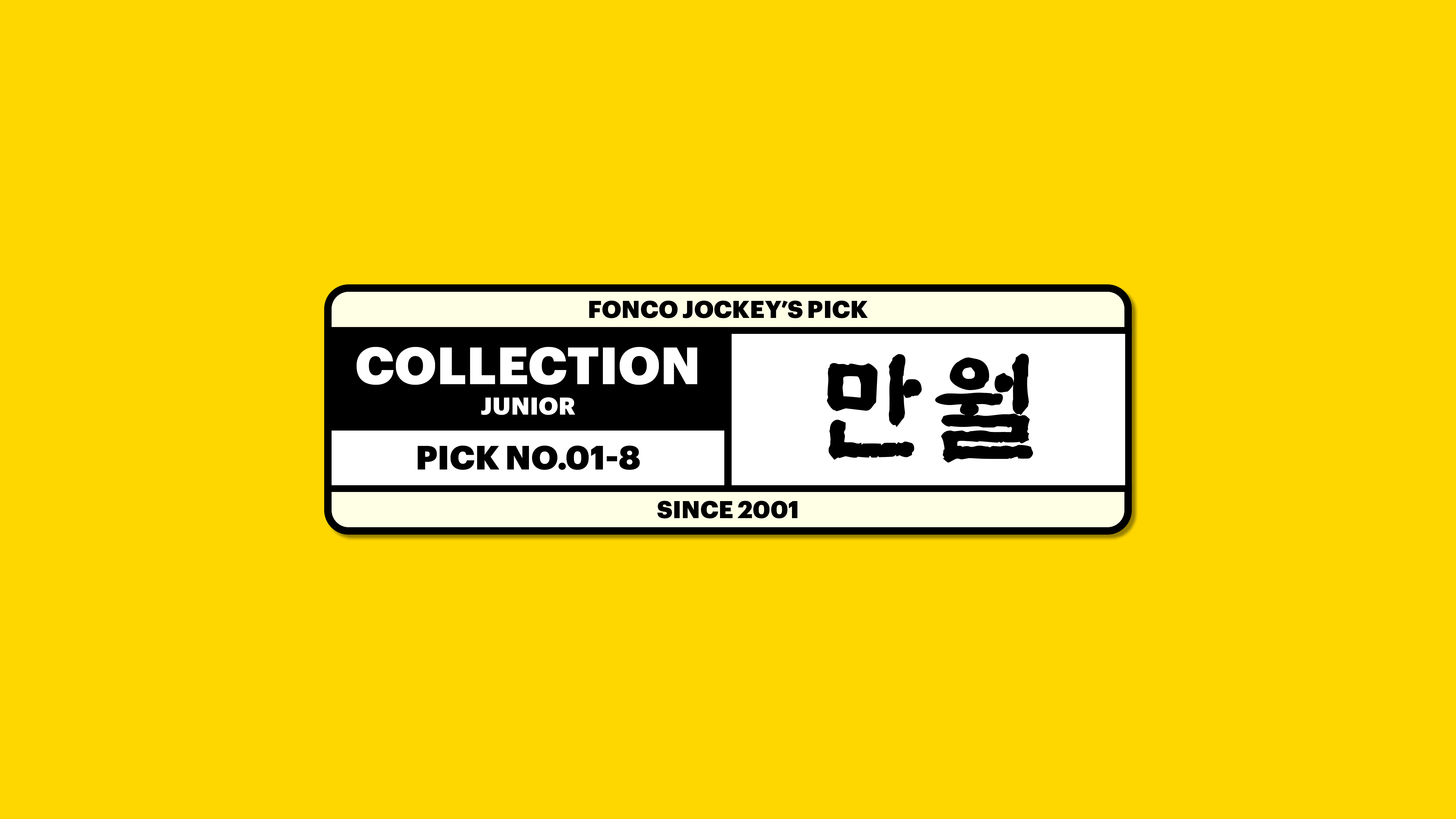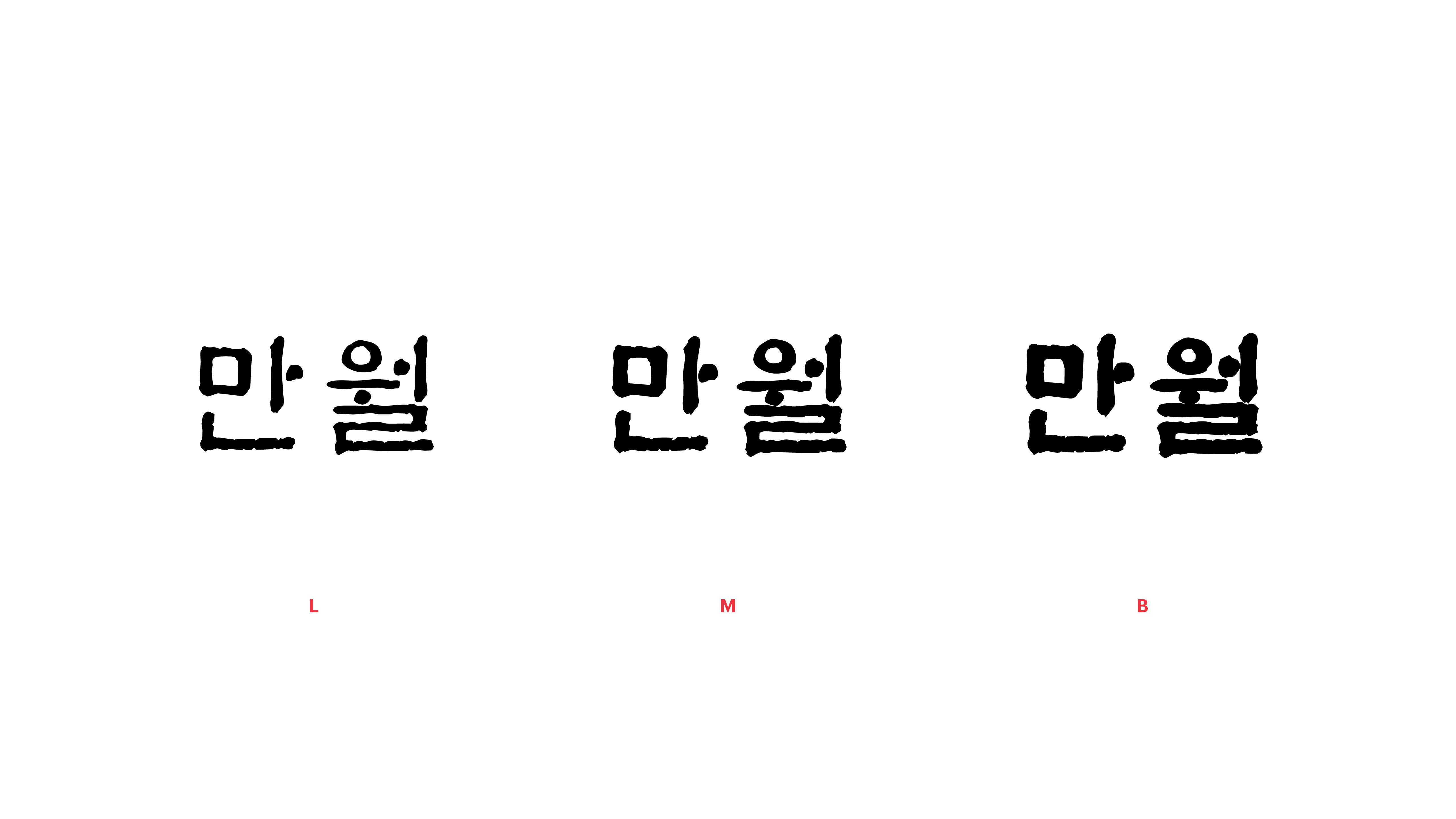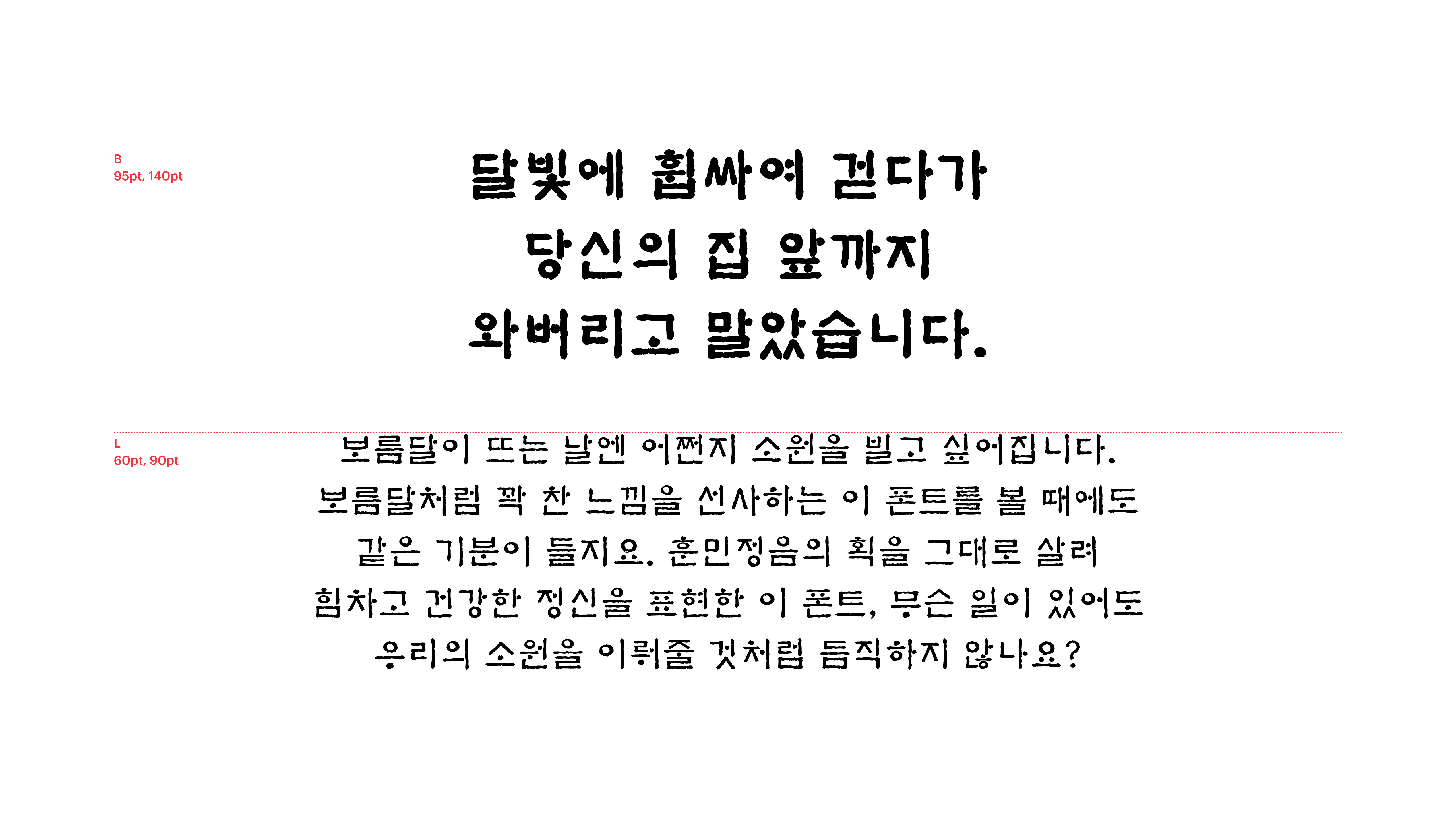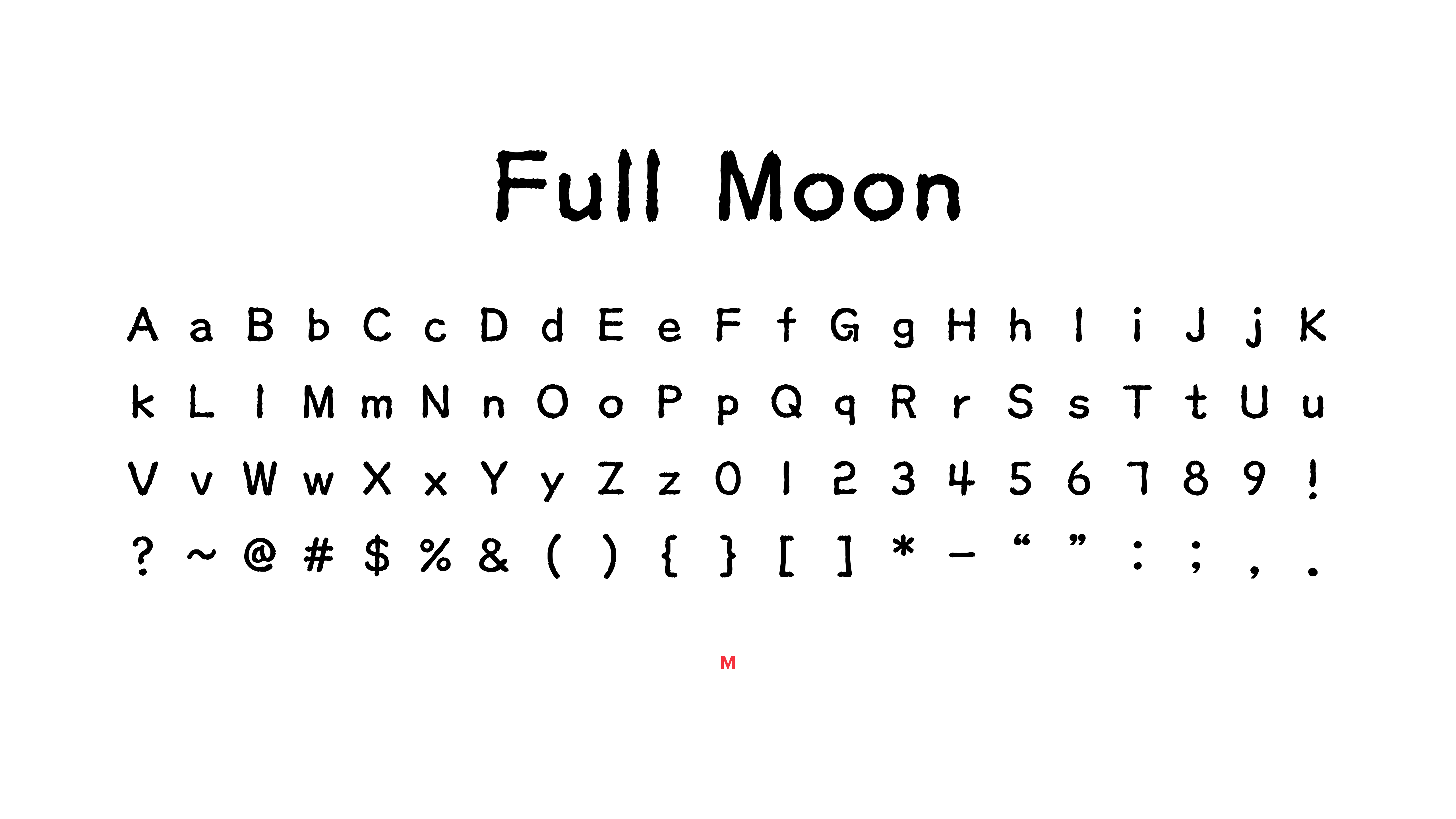
[손글씨]
만월
Yoon 만월
보름달이 뜨는 날엔 어쩐지 소원을 빌고 싶어집니다. 보름달처럼 꽉 찬 느낌을 선사하는 이 폰트를 볼 때에도 같은 기분이 들지요. 훈민정음의 획을 그대로 살려 힘차고 건강한 정신을 표현한 이 폰트, 무슨 일이 있어도 우리의 소원을 이뤄줄 것처럼 듬직하지 않나요?